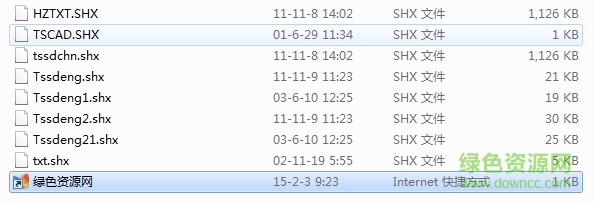
tssd rein字體是一份cad的鋼筋符號字體,很多人的圖紙顯示亂碼及時缺少該字體,事實上tssd rein并不是一款字體,而是字體樣式,大家只需要下載tssd字體,然后進去定義一下就行了。
tssd-rein字體實際上是Tssding字體里面的一個分項,Tssding里還有tssd-nomal等多種tssd字體名。小編這里提供了cad結(jié)構(gòu)必用字體,包括了多款tssd字體文件。